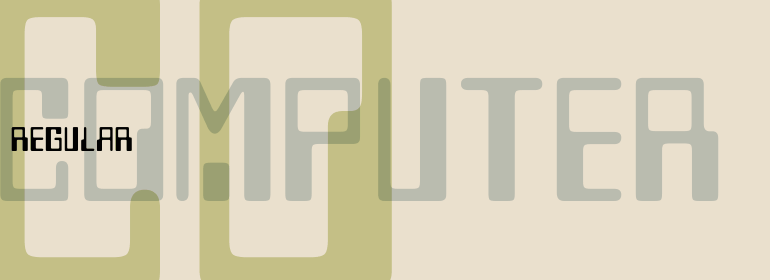
Computer
Computer,这款字体结构工整、笔画清晰,兼顾美观与易读性,适用于标题、正文、海报、包装、LOGO 等多种场景。字形优雅稳定,风格百搭耐看,适配日常排版与创意设计,让文字呈现更舒适、更具质感。Computer一笔一画,皆是细节,以均衡的比例、流畅的线条打造舒适视觉体验,字形端正大气,风格简约现代。无论是商业设计、品牌宣传还是日常排版,都能轻松驾驭,让文字更有格调与力量。Computer字体下载。